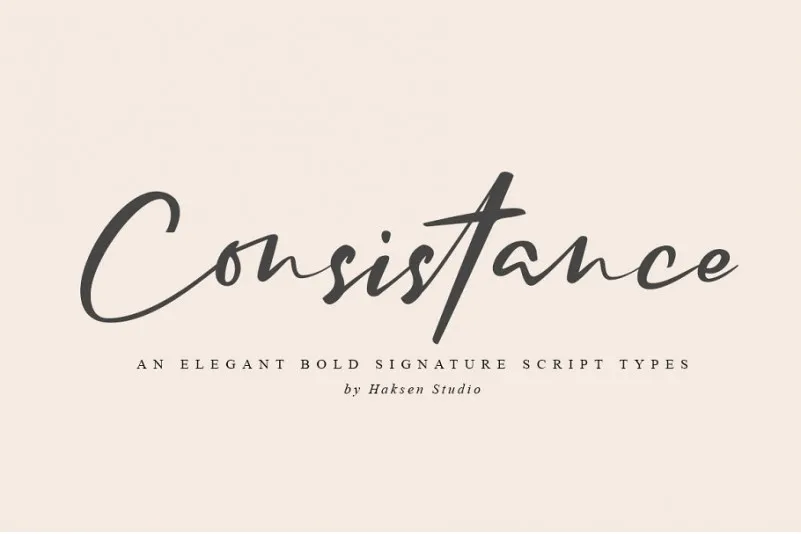
Consistance Signature Font – Fonte Grátis
Consistance Signature Font
Caros criativos, estou aqui uma nova fonte de letra assinatura com acento, perfeitamente adequada para qualquer projeto visual que deseje dar um toque moderno e elegante. Introduzimos a Consistance Signature Font, uma fonte handwritten criada pelo designer Haksen. Ela apresenta os elementos desejáveis para branding, cartões de convidados e convites de casamento, bem como pode ser usada em rótulos de vinho. E não se limite ao design impresso; ela é perfeita para logo design, coberturas de jornal, revistas, cartas de cumprimento, frases e muito mais. Esta fonte moderna e natural foi projetada com um estilo casual e reto, uma combinação única que a torna perfeitamente adaptável às demandas do mercado atual. Seja em seu site, sua identidade visual ou até mesmo em rótulos de vinho, esta Consistance Signature Font irá oferecer ao seu design um toque diferenciado e elegante sem perder a essência natural da escrita manual. Se você está à procura de uma fonte que possa trazer um pouco mais de personalidade para seus projetos, então não deixe passar pela Consistance Signature Font. Essa fonte é exatamente o que você precisa.